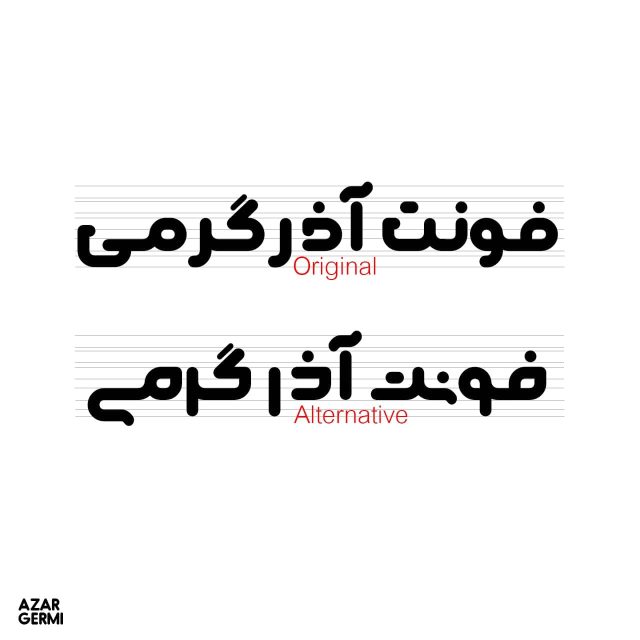
دانلود فونت فارسی آذرگرمی Azargermi Font
AzarGermi 2 1فونت فارسی آذرگرمی آپدیت شد!
*فونت آذرگرمی* با استایلی جدید و حروف آلترناتیو به‌روزرسانی شد. *فونت آذرگرمی* اثر هاشم شهرزاد یک فونت هندسی، فانتری است که با ویژگی افزایش حد سفیدخوانی در حروف بالای خط کرسی، مخاطب را ترغیب به خوانش متن کرده و در این راه سرعت خواندن متن را افزایش می‌دهد. این تایپ فیس جدید را می توانید هم اکنون از سایت دیاکوگرافیک به صورت قانونی خریداری و دانلود کنید که توسط طراح فونت یعنی آقای شهرزاد برای فروش در سایت ما قرار داده شده است همچنین پس از خرید می توانید از پشتیبانی طراح فونت نیز به مدت ۶ ماه کاملا رایگان استفاده کنید.
*فونت فارسی آذرگرمی* دارای ضخامت یکسان بوده و با ایجاد فضای باز زیاد در حروف دهانه‌دار، حس سبکبالی را در چشم بیننده القا می‌‌کند. *امروزه فونت‌های فانتزی بسیار محبوب هستند و از آنجایی که لوگوهای فارسی بیشتر در سبک لوگوتایپ طراحی می‌شوند، از فونت آذرگرمی می‌توان برای طراحی لوگوتایپ و موارد دیگر استفاده کرد. *فونت آذرگرمی* با این ویژگی‌ها بسیار مناسب طراحی گرافیک محیطی مانند تابلوهای راهنما، سر در مغازه‌ها، ایستگاه‌های مترو، بیلبوردهای تبلیغاتی، وسایل در حال حرکت مانند کامیون و اتوبوس و مترو است.
*فونت آذرگرمی* به صورت تک وزن Bold طراحی شده است که علاوه بر تمام حروف و اعداد فارسی، از حروف عربی و لاتین در شکل و سایز متناسب پشتیبانی می‌کند که هنگام قرارگیری این دو تایپ در کنار یکدیگر زیبایی خاصی به وجود می‌آید.
*نکته: (برای استفاده از حروف آلترناتیو در ویندوز از دکمه‌های shift+m و m و در گوشی‌های اندرویدی از (ء) و (ئ) استفاده کنید.